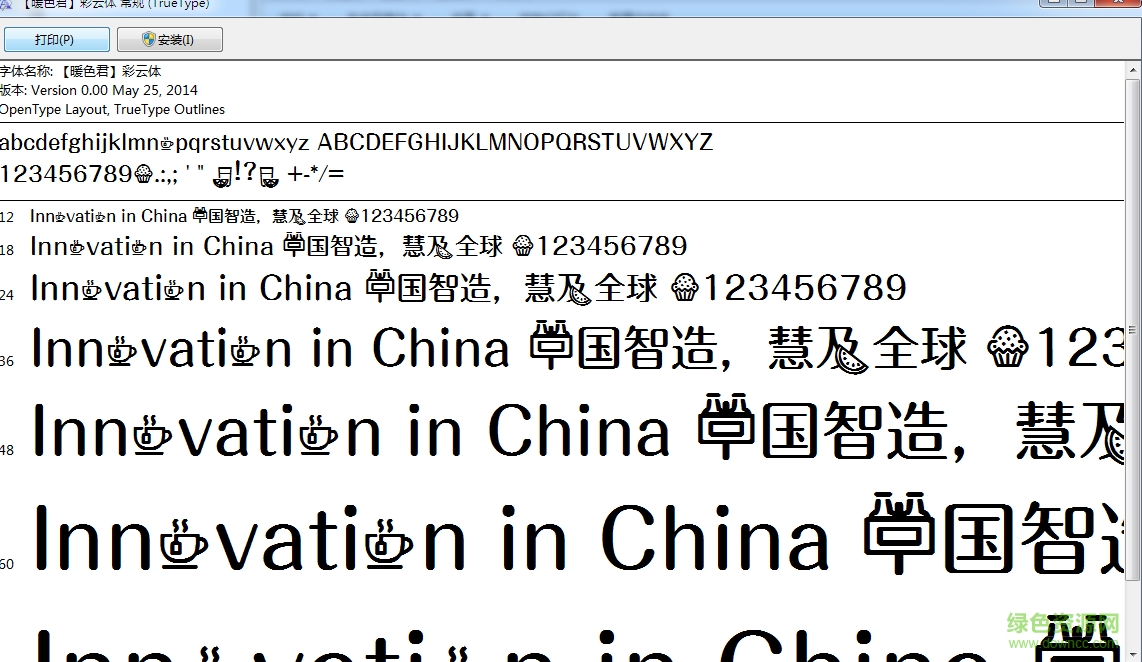
暖色君彩云体字体是一款非常有特色的字体,字体中加入了水果、冰淇淋等特色,看上去非常的萌,用来制作各种各种可爱的设计再适合不过了,喜欢的朋友欢迎来了绿色资源网下载!
暖色君彩云体是一款萌萌哒字体,字形粗黑可爱,笔画清新洒脱,整体散漫随意,识别度非常高,字体糅合了小动物头像、爱心、圆圈、冰淇淋等各种可爱的元素,非常适合用来制作个性签名!